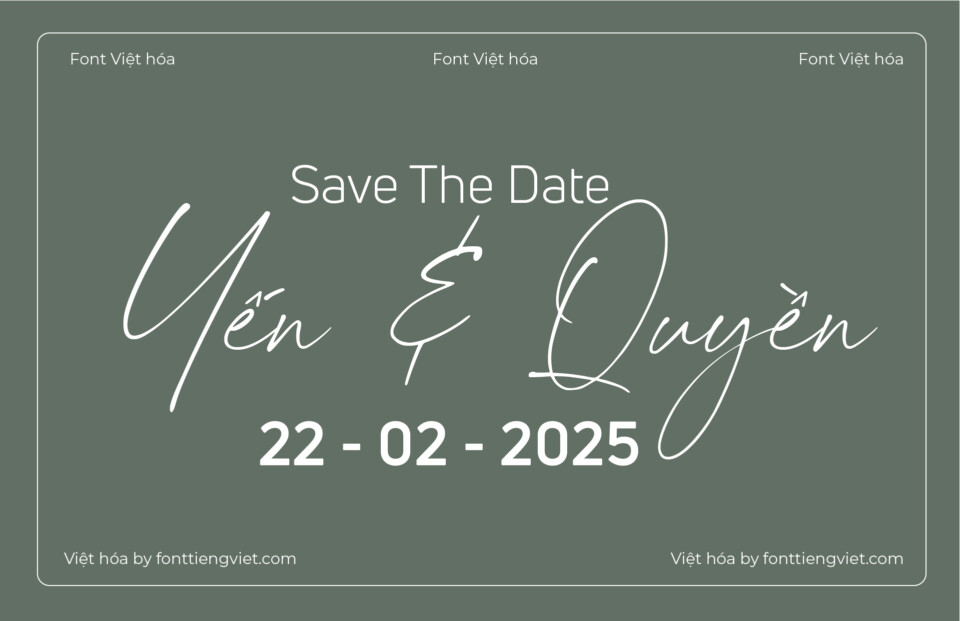
Trong thế giới thiết kế đồ họa hiện đại, việc tìm kiếm một bộ Font Chữ vừa mang nét truyền thống vừa giữ được sự sang trọng là điều không hề dễ dàng. Bộ Font Việt hóa 1FTV VIP The Artisan xuất hiện như một giải pháp hoàn hảo, giúp các bạn học sinh và giáo viên tạo ra những ấn phẩm học đường đầy tính nghệ thuật. Đây là một phông chữ được tinh chỉnh kỹ lưỡng, hỗ trợ đầy đủ bộ gõ tiếng Việt, giúp loại bỏ hoàn toàn lỗi hiển thị ký tự khi soạn thảo văn bản hay thiết kế slide bài giảng.
Đặc điểm nổi bật của Font Việt hóa 1FTV VIP The Artisan
Vẻ đẹp thủ công và tinh tế
Font Việt hóa 1FTV VIP The Artisan mang phong cách “Artisan” đúng nghĩa với những đường nét uốn lượn tự nhiên, gợi liên tưởng đến những tác phẩm viết tay của các nghệ nhân. Sự kết hợp giữa nét thanh và nét đậm tạo nên sự cân bằng thị giác tuyệt vời, giúp nội dung trở nên thu hút và dễ đọc hơn. Đây là lựa chọn lý tưởng cho các tiêu đề báo tường, thiệp chúc mừng hoặc các biểu ngữ trang trí trong trường học.
Khả năng ứng dụng linh hoạt trong học tập
Không chỉ dừng lại ở tính thẩm mỹ, bộ font này còn có độ tương thích cao với nhiều phần mềm phổ biến như Word, PowerPoint và Photoshop. Nhờ việc được việt hóa chuẩn xác, người dùng có thể yên tâm sử dụng Font Việt hóa 1FTV VIP The Artisan để thể hiện những nội dung tiếng Việt có dấu một cách mượt mà nhất. Sự chỉn chu trong từng con chữ sẽ giúp các bài thuyết trình của học sinh trở nên chuyên nghiệp và ấn tượng hơn trong mắt thầy cô.
Hướng dẫn sử dụng và kết luận